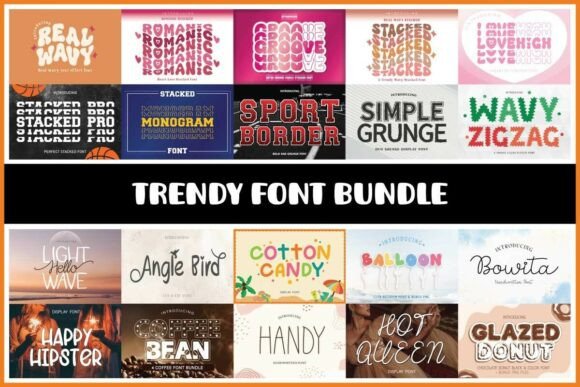
Trendy Font Bundle
Trendy Font Bundle와 같은 κ³ ν’ˆμ§ˆ μžμ‚°μ„ μ°Ύκ³  μžˆλ‹€λ©΄ 이 프리미엄 νŒ¨ν‚€μ§€λŠ” 창의적인 ν”„λ‘œμ νŠΈλ₯Ό μœ„ν•œ ν™˜μƒμ μΈ μ„ νƒμž…λ‹ˆλ‹€.
POD(μ£Όλ¬Έν˜• 인쇄) μ œν’ˆ, κ²°ν˜Όμ‹ μ΄ˆλŒ€μž₯ λ˜λŠ” μ†Œμ…œ λ―Έλ””μ–΄ κ·Έλž˜ν”½μ„ λ§Œλ“€ λ•Œ Trendy Font BundleλŠ” 이상적인 μ„ νƒμž…λ‹ˆλ‹€.